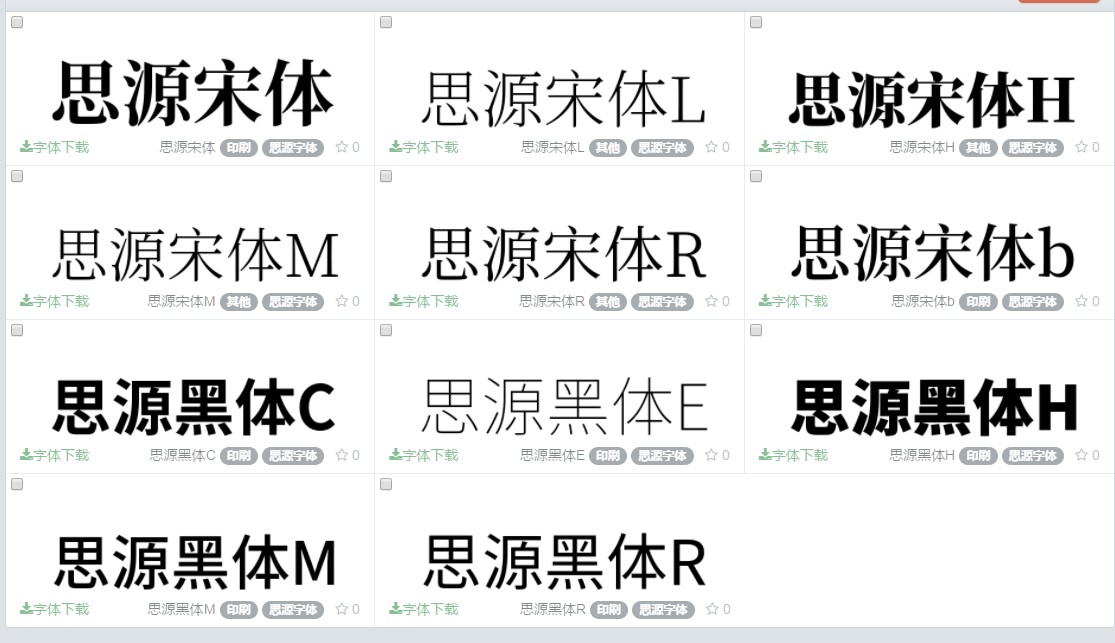
饮水思源,思源字体,一款真正良心的免费可商用字体
思源黑体是Adobe与Google历时三年在2014年7月宣布推出的一款开源字体,这是一款新的供桌面使用的开源 Pan-CJK 字体家族, 有七种字体粗细(ExtraLight、Light、Normal、Regular、Medium、Bold 和 Heavy),完全支持繁体中文、简体中文、日文和韩文,这些全部都包含在一种字体中。它还包括来自我们颇受欢迎的 Source Sans字体家族的拉丁文、希腊文和西里尔文字形。
思源宋体
思源黑体H